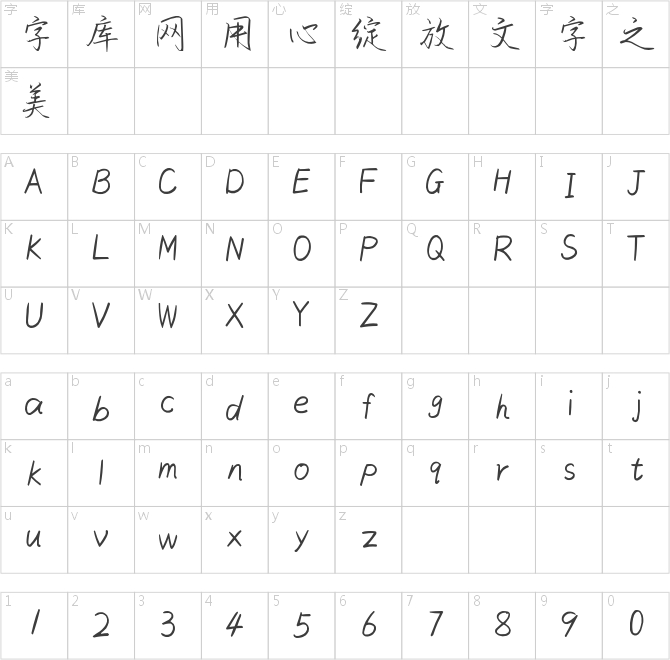
高冷面癱-摩羯座有著硬筆書法字的特點(diǎn),筆畫流暢,用筆張弛有度、從容不迫,深具書寫之美感。適用于文藝類的書刊、品牌廣告和產(chǎn)品包裝設(shè)計(jì),以及社交網(wǎng)絡(luò)的個(gè)性化用字。
高冷面癱-摩羯座 字體字庫是一款讓人賞心悅目、百看不厭的中文字體,適合各類廣告和產(chǎn)品包裝設(shè)計(jì)應(yīng)用,字體大小11.11MB,格式為TTF字體,上傳用戶是秦立華,作者/版權(quán)方為方正手跡